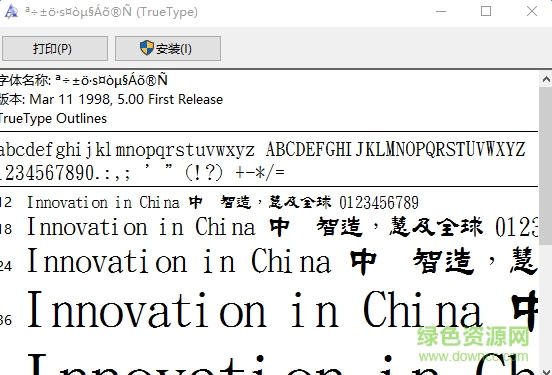
金梅新毛筆隸書字體是金梅字庫中的一款很好用的毛筆字體,這款字體寫出來的字是很好看的,大氣、美觀,有著自己獨(dú)特的魅力,喜歡的朋友就快來綠色資源網(wǎng)下載吧。
金梅新毛筆隸書字體這款字體是真的很不錯(cuò)哦,小編已經(jīng)幫大家試用過了,寫出的效果是非常的好,大家一定要試試看哦。